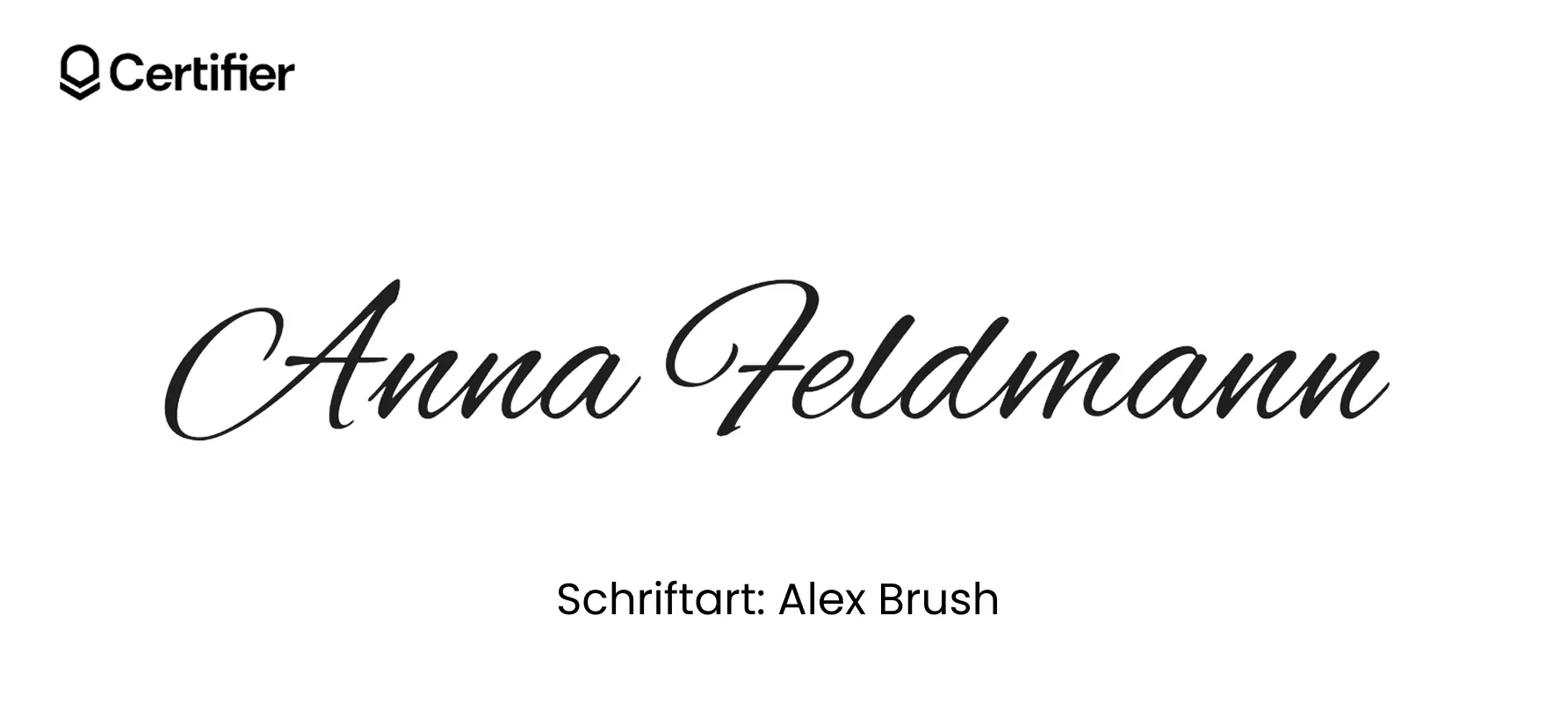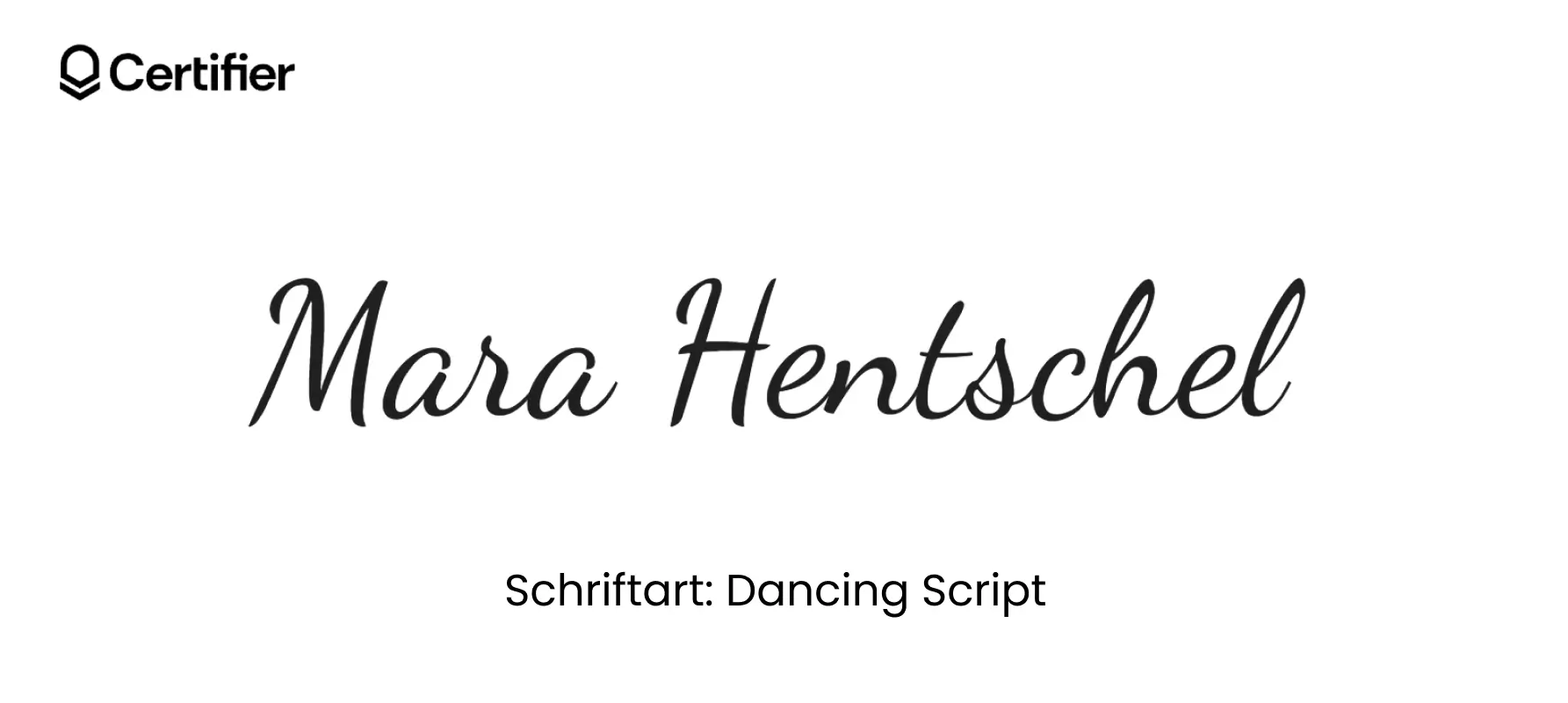
Times New Roman oder serifenlose Schriftarten sind solide Klassiker – beliebt, aber wenig persönlich. Doch wenn es um deine eigene digitale Unterschrift geht, brauchst du mehr Ausdruck.
Schwungvolle Linien, ein moderner Kalligrafie-Stil und leichte Unregelmäßigkeiten, die echte Handschrift nachahmen. Zu formelle oder zu gleichmäßige Schriftarten wirken nie authentisch auf deinen Zertifikaten.
01 Alex Brush
Alex Brush ist eine elegante Schriftart wie Unterschrift – ideal für Zertifikate und digitale Dokumente. Perfekte Schriftart für Unterschrift in Word, stilvoll und kostenlos.
Alex Brush ist eine elegante Schriftart Unterschrift – ideal für Zertifikate und digitale Dokumente. Perfekte Schriftart für Unterschrift Word, stilvoll und Schriftart Unterschrift kostenlos.
Verleihe jedem Dokument einen Hauch von Eleganz mit dieser Schriftart. Alex Brush wirkt edel und harmoniert hervorragend mit hellen wie dunklen Hintergründen – einfach die Schriftfarbe an dein Design anpassen.
Wenn du elegante oder formelle Zertifikate ausstellen möchtest, ist Alex Brush eine ausgezeichnete Wahl.
Neben Zertifikaten entfaltet ihre schwungvolle Pinsel-Kalligrafie auch Wirkung bei:
Hochzeitseinladungen
Produktverpackungen
Visitenkarten
Materialien für Personal Branding
Beiträgen in sozialen Medien
Ihr fließender Stil macht Alex Brush zu einer der elegantesten und vielseitigsten Schriftarten für Unterschrift überhaupt.
02 Birthstone
Birthstone ist eine stilvolle Schriftart Unterschrift kostenlos – sie kombiniert moderne Kalligrafie mit natürlicher Handschrift.
Diese fast kursiv wirkende Schrift passt perfekt zu jeder Art von Dokument – ob Zertifikate, formelle Einladungen, Logo-Designs mit Signatur oder kreative Projekte mit persönlicher Note.
Birthstone verbindet traditionelle Kalligrafie mit einem modernen Flair und eignet sich daher ideal für viele Anwendungsbereiche – von kreativen Projekten über Unternehmensdesigns bis hin zu Grußkarten.
Für alle, die eine Schriftart wie Unterschrift suchen, überzeugt Birthstone durch ihre natürliche, authentische Linienführung. Sie sieht aus wie deine eigene Handschrift – nur etwas stilvoller.
03 Dancing Script
Dancing Script ist eine schwungvolle Schriftart wie Unterschrift, die sich ideal für Zertifikate eignet; diese Schriftart für Unterschrift Word wirkt professionell und persönlich.
Dancing Script bringt Leben und Bewegung in jeden Text. Mit ihren weichen Schwüngen verleiht sie deiner digitalen Unterschrift und dem gesamten Zertifikatsdesign eine elegante Ausstrahlung.
Auch in E-Mail-Signaturen funktioniert sie hervorragend – sie wirkt persönlich und gleichzeitig professionell. Der Kontrast zwischen den verspielten Kleinbuchstaben und den klaren Großbuchstaben sorgt für ein dynamisches, ansprechendes Schriftbild.
Diese Schriftarten sehen aus wie handgeschrieben, wirken persönlich und lassen sich direkt in Google Docs oder Zertifikat-Vorlagen verwenden.
Wenn Sie eine Schriftart wie Unterschrift suchen, die kostenlos, stilvoll und einfach integrierbar ist, sind diese Optionen ideal – auch als Schriftart für Unterschrift Word geeignet.